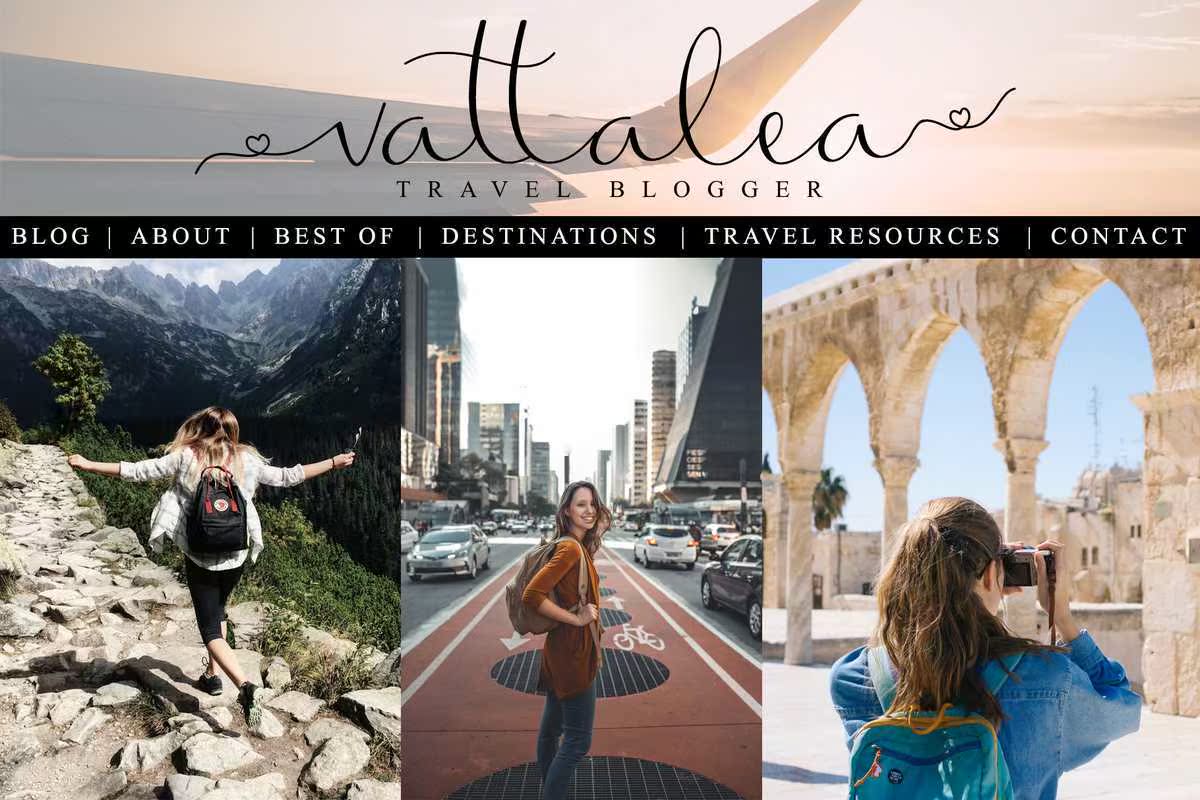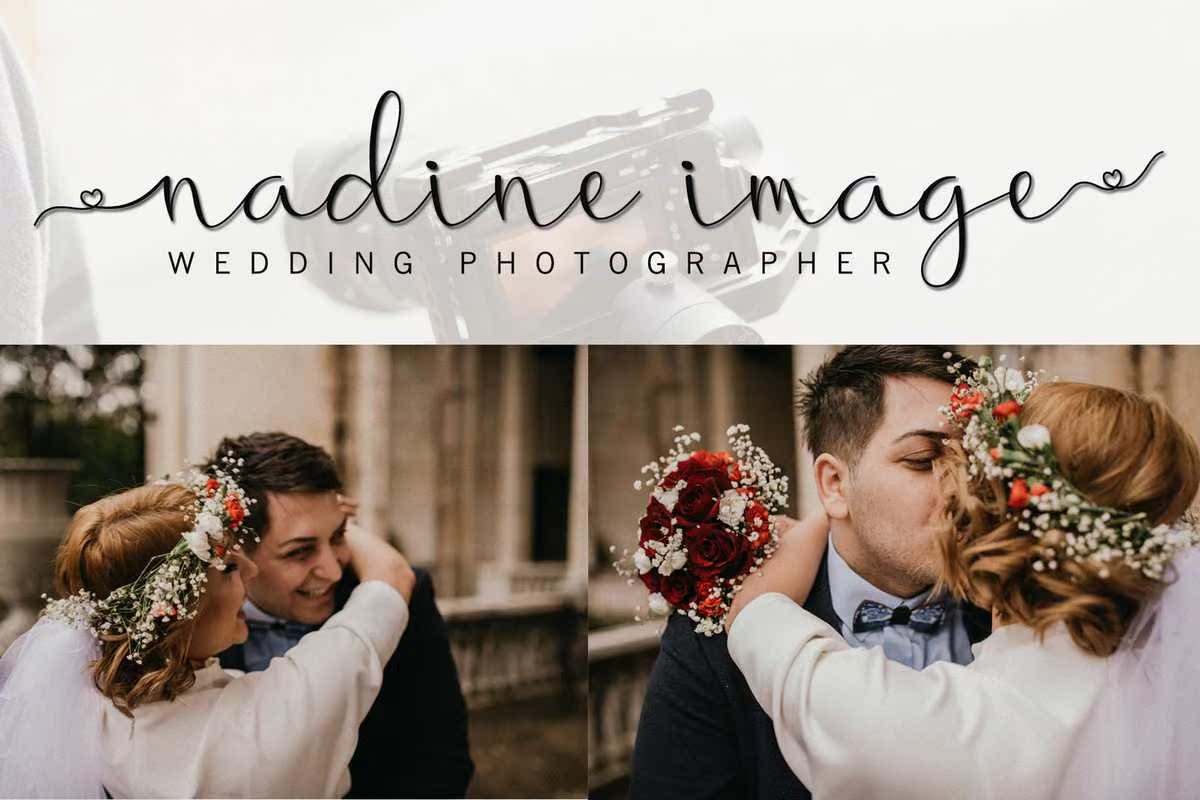
AllodyAisa和WritenScript字体,带有Legant和BeautifulLook。AllodyAisa和WritenScript字体,带有Legant和BeautifulLook PerfectforLegant徽标、婚礼统计表、海报、报价,以及任何其他需要手写的项目。AllodyAisa和WritenScript字体,带有Legant和BeautifulLook。AllodyAisa和WritenScript字体,带有Legant和BeautifulLook,短文本、品牌、网页、图形设计和任何其他需要手写的项目。